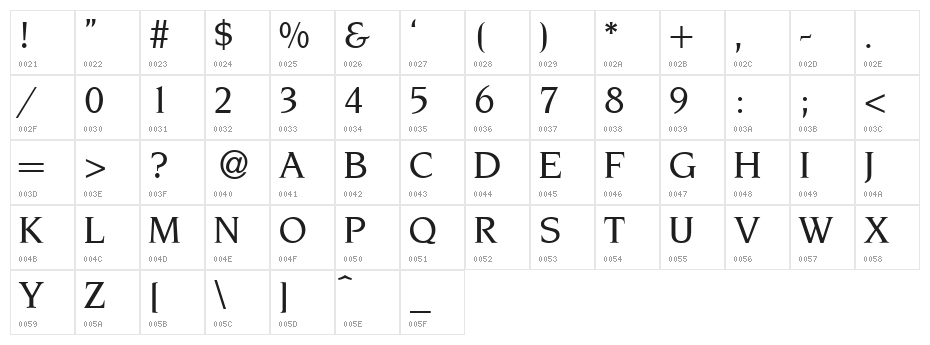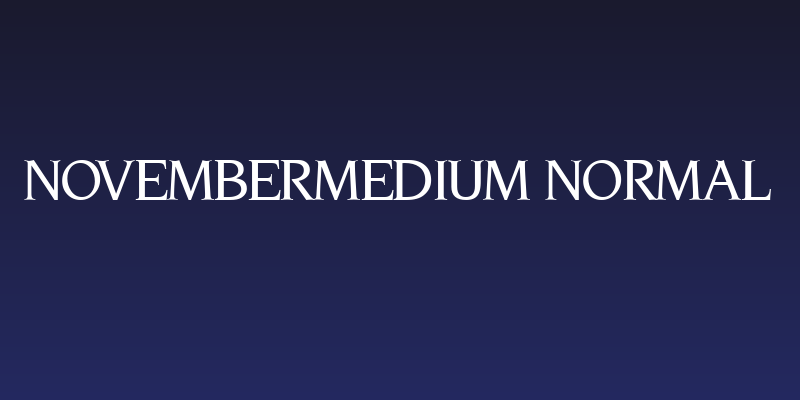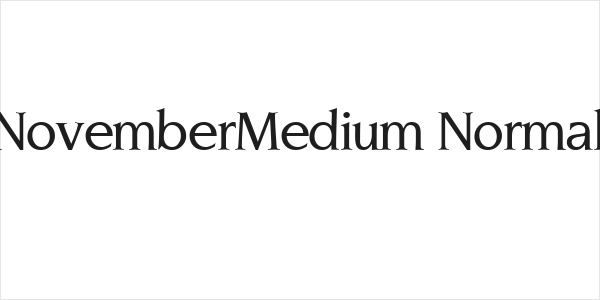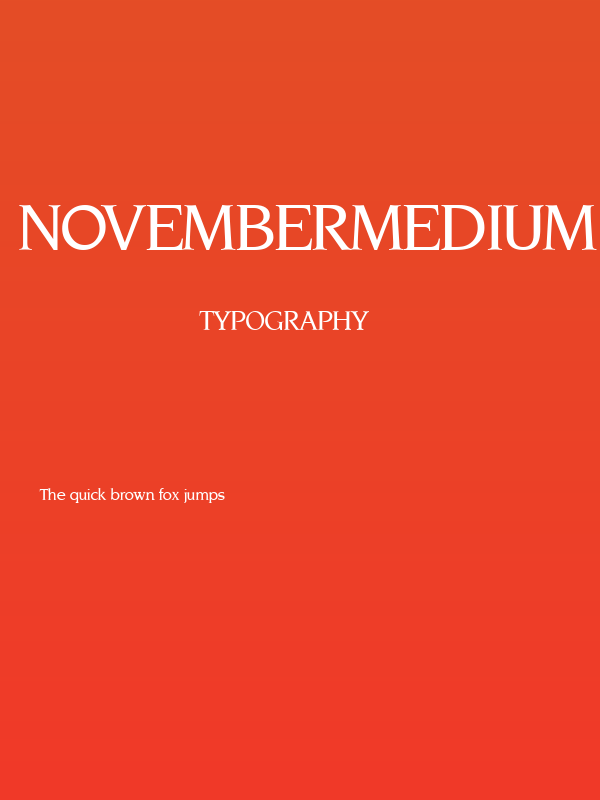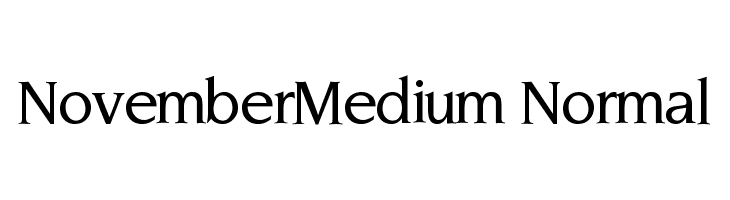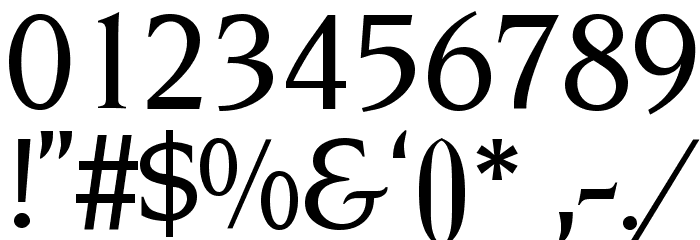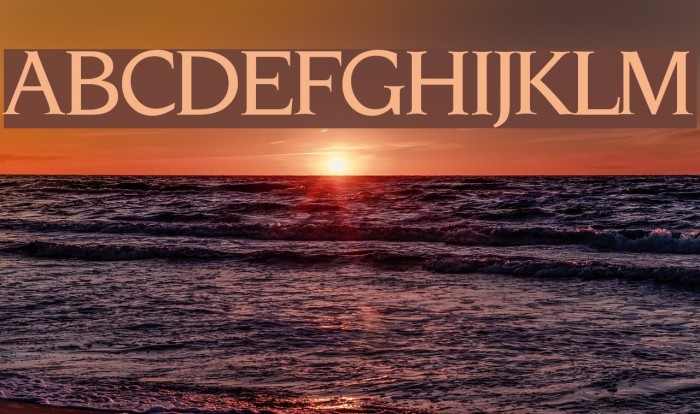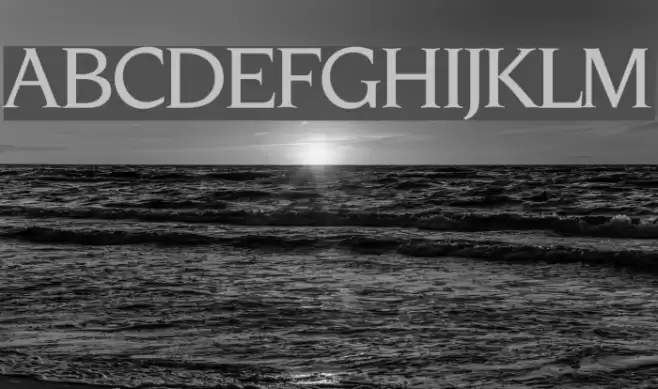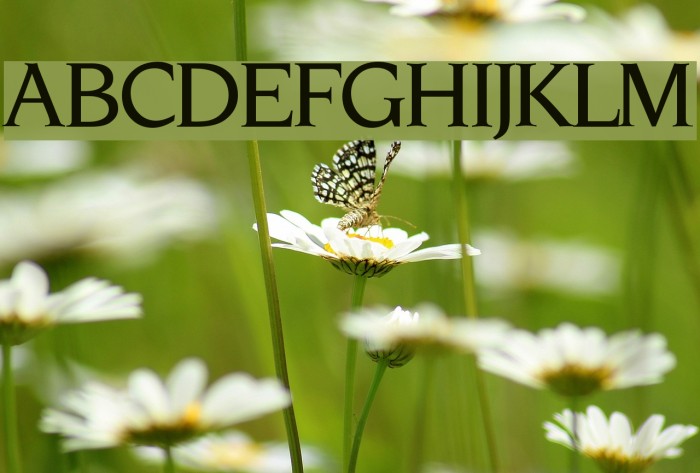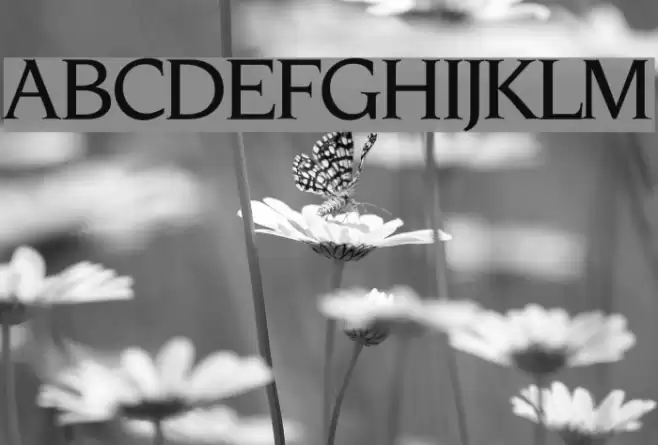
NovemberMedium Normal Font
| Gesamtstil | Classic |
| Anwendungsfall | Headlines, Body text, Logos |
| Vorgeschlagene Projekte | Ideal for editorial design, book covers, formal invitations, and branding projects that require a touch of sophistication. |